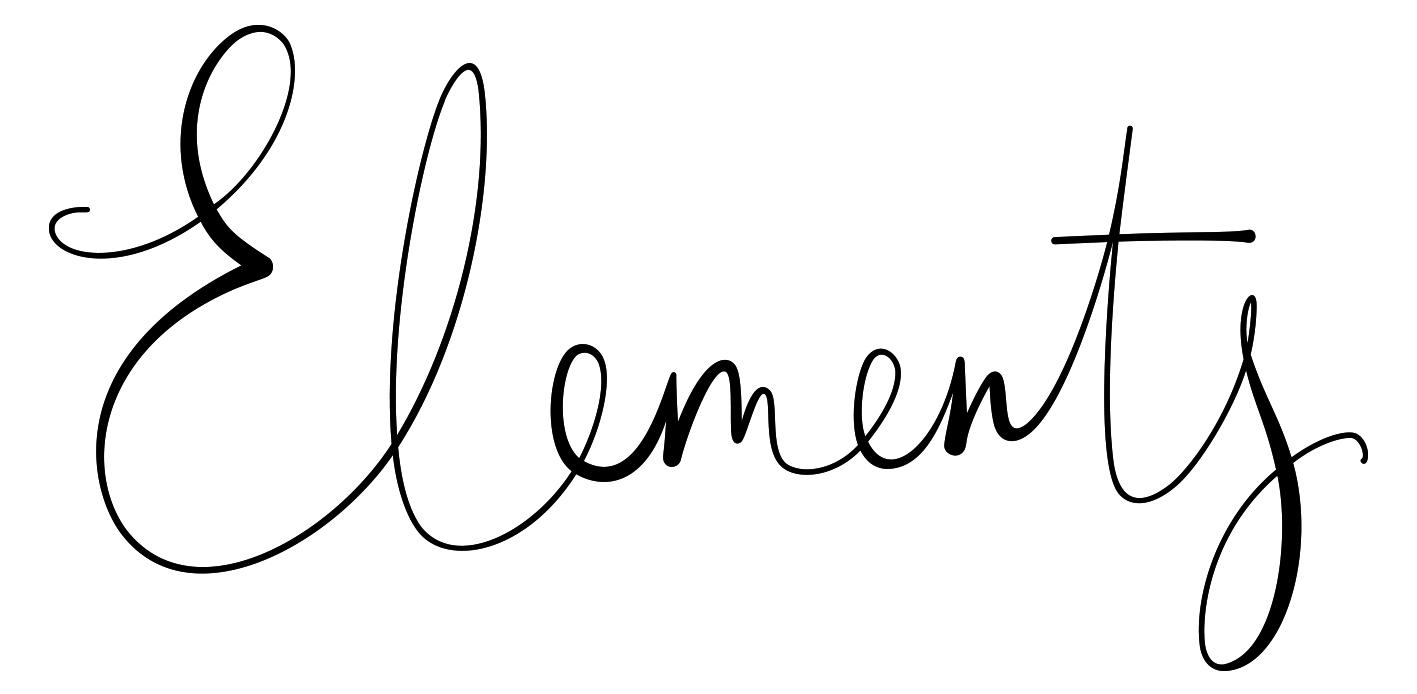
Schrifterkennung (Elements)
kennt jemand diese Schrift?
Mit Schrifterkennungstools wie whatthefont etc. bin ich leider nicht weitergekommen...
Das ist nicht aus einer Schrift gesetzt, sondern von Hand gefertigt. Die unterschiedlichen Höhen und Dicken der Buchstabenanschlüsse können in einem Font so nicht angelegt werden.